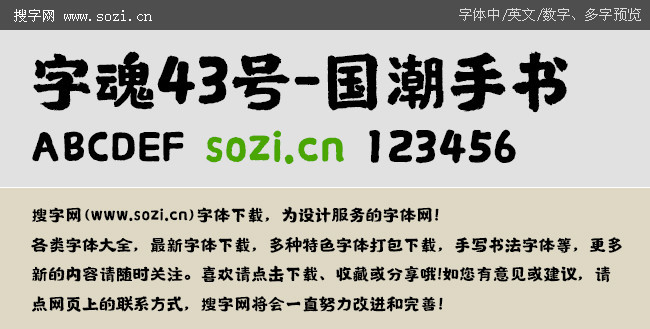
字魂43號-國潮手書
搜字網(wǎng)提供一款字魂43號-國潮手書中文字體下載,該字體是一款毛筆書法手寫字體,該字體包含6763個中文、字母、 符號和數(shù)字,具有有力、穩(wěn)重、古典、中國風 的風格,可以滿足您設(shè)計上的各種需求,該字體主要用于企業(yè)店鋪、廣告、包裝、雜志、電商 等場景。